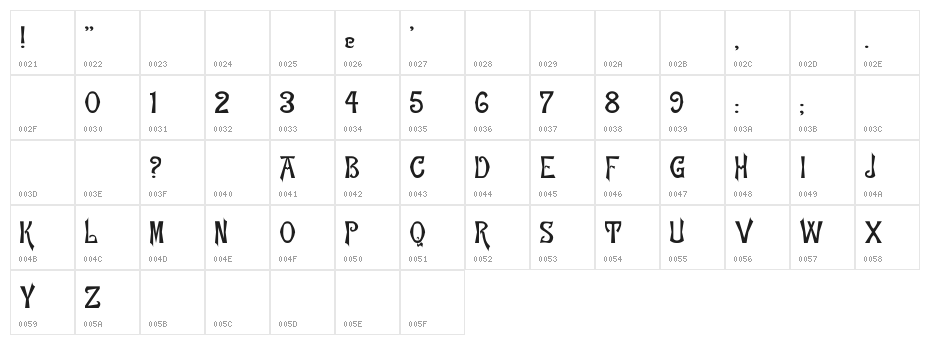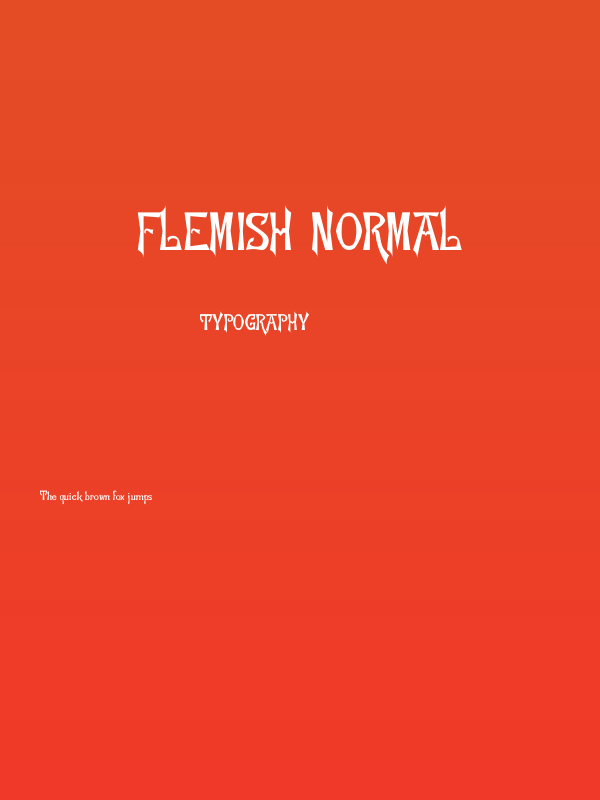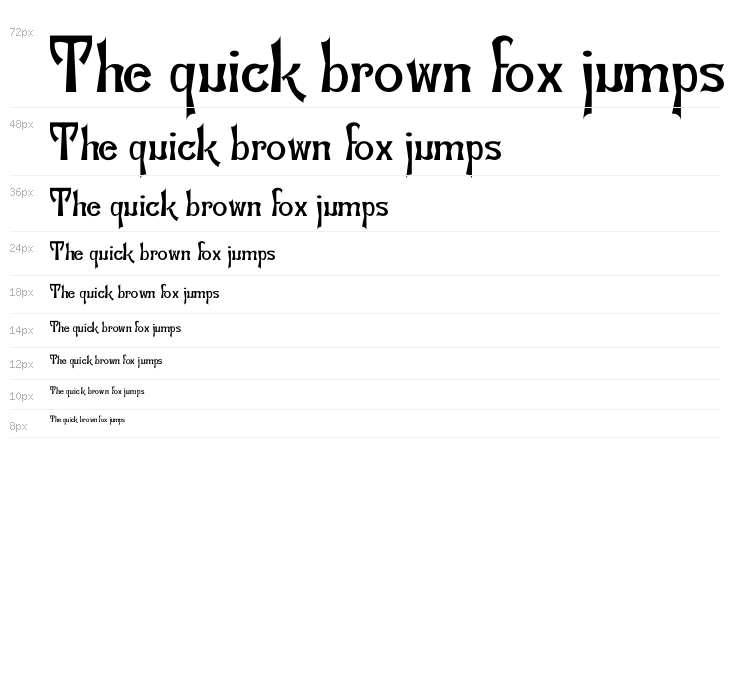
Flemish-Normal Font
| Stil general | Gothic, Medieval, Decorative |
| Proiecte propuse | Ideal for fantasy book covers, historical event posters, themed invitations, or any project requiring a medieval or gothic touch. |